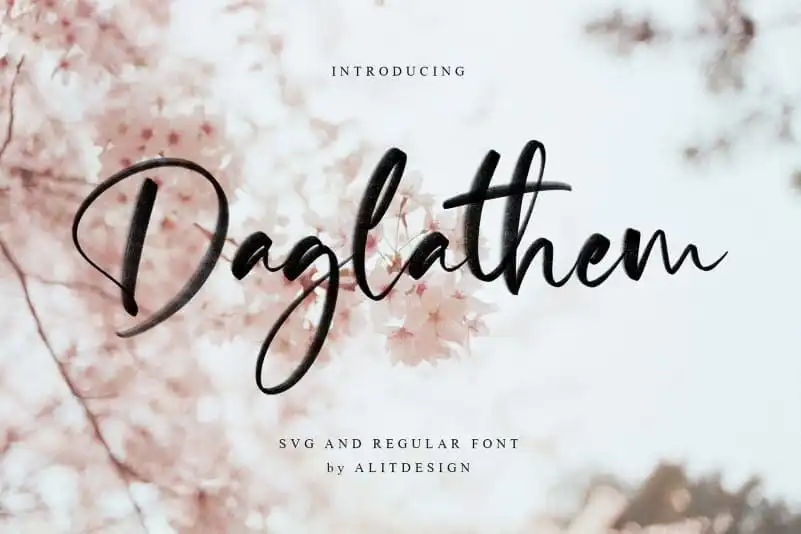
Daglathem Brush Font – Fonte Grátis
Daglathem Brush Font
A Daglathem Brush Font é uma nova tipografia Script criada com a lâmina de caneta calligrafia, projetada para manter sua naturalidade e oferecer um impressionante efeito de escrita à mão, perfeita para uso em designs de convites de casamento. Este tipo de fonte SVG, chamado Fonte de Escrita Script Hidratada, transmite uma paixão tropical através do conceito incorporado nas letras individuais. Perfumada com o encanto da tipografia em cada característica, a Daglathem Brush é perfeita para criar impressionantes citações impressas, convites de casamento, headlines nas redes sociais, embalagens de produto e muito mais. Essa fonte oferece um toque autêntico que combina bem com designs contemporâneos, sem perder sua elegância natural característica da tipografia script.